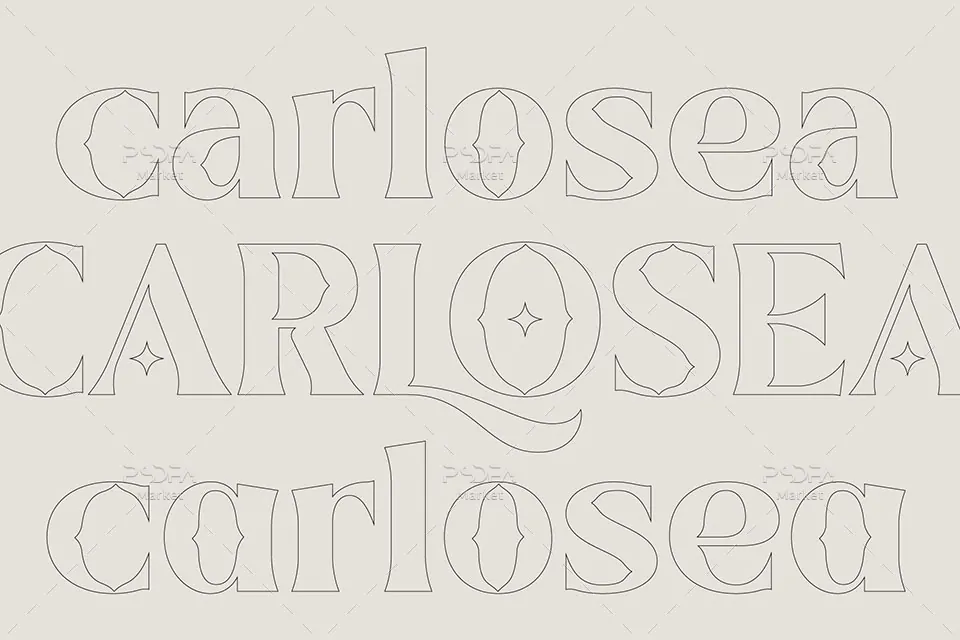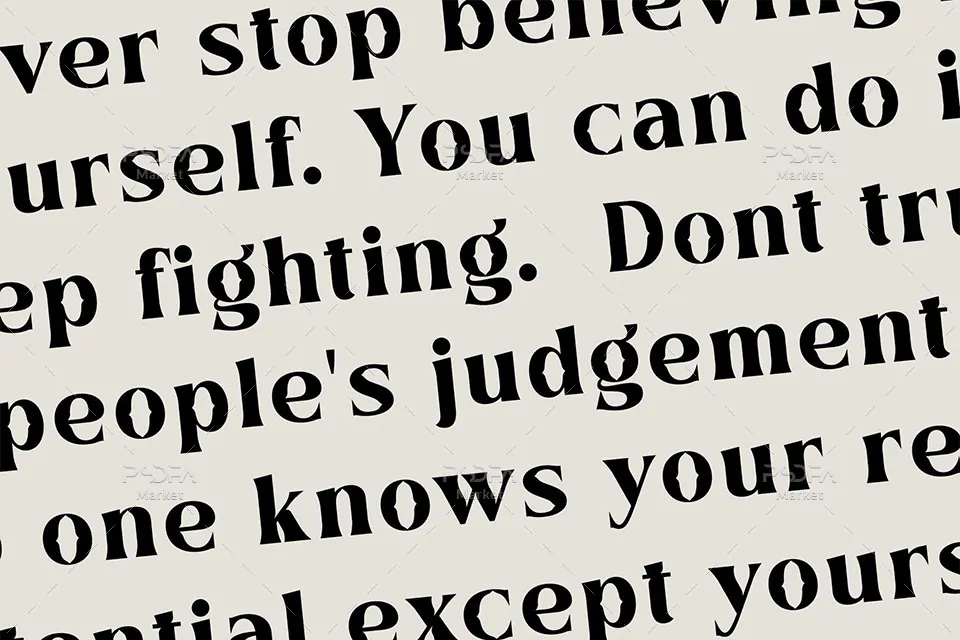
سریف فونت انگلیسی کلاسیک و قدیمی Carlosea
سریف فونت انگلیسی کلاسیک و قدیمی Carlosea یک قلم فوق العاده زیبا است که مناسب جهت استفاده در طرح و پروژههای گرافیکی مختلف میباشد. این فونت زیبا در قالب فایلهای OTF, TTF در فایل محصول قرار دارد که با نصب یکی از این 2 فرمت در پوشه فونتهای سیستم میتوانید از این فونت انگلیسی در تمام نرم افزارهای گرافیکی و تایپ متون همچون فتوشاپ، افتر افکت، پریمیر، ورد، پاورپوینت و … استفاده کنید.
فونت سریف Carlosea در وزن معمولی (Regular) طراحی شده است که میتوانید از آن در طراحی انواع پوستر، بسته بندی محصولات، لوازم التحریر، بگهای خرید و هدیه، ظروف یکبار مصرف، تقویم، بنر، بروشور، تراکت و دیگر طرحهای گرافیکی استفاده کنید.